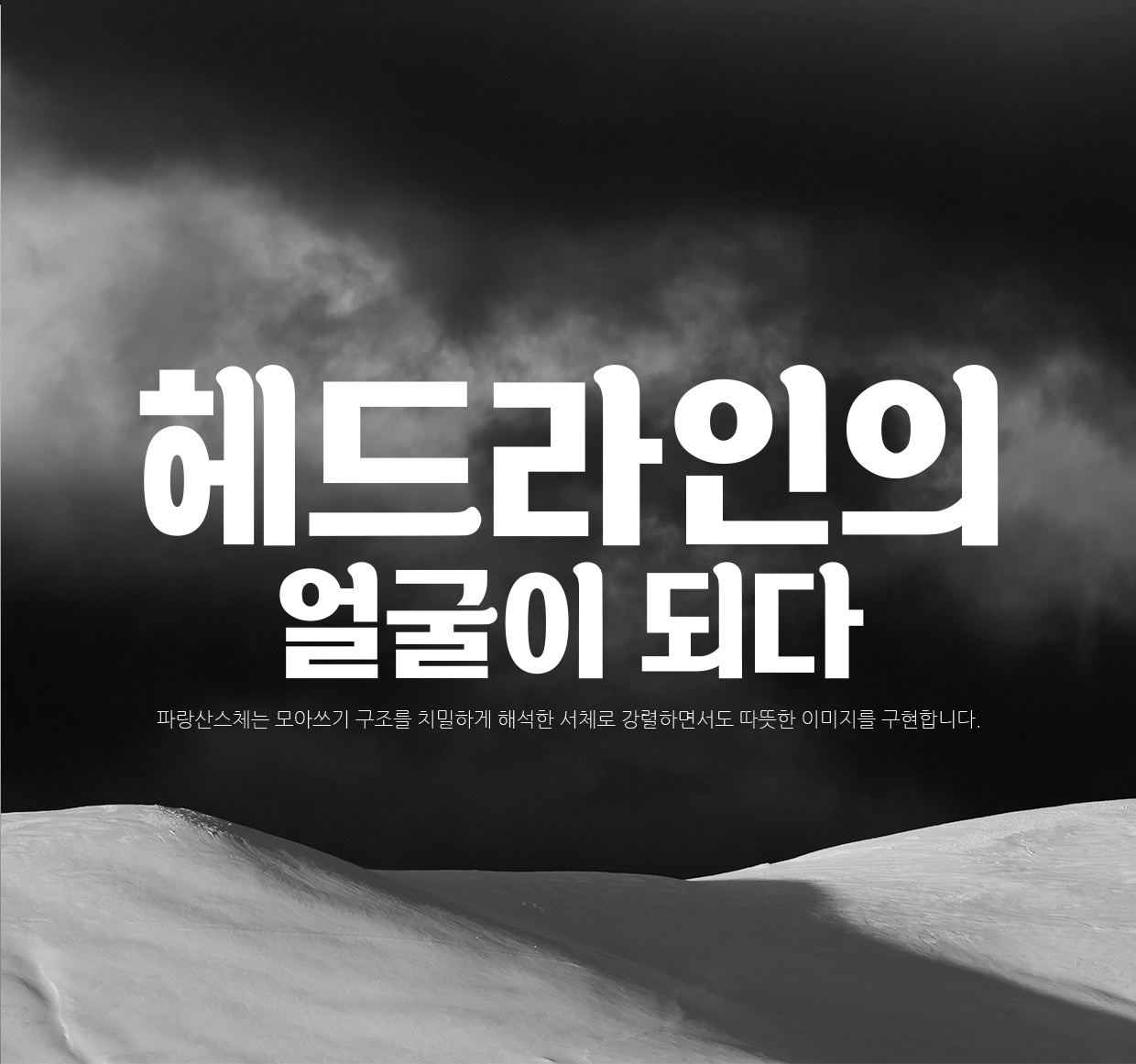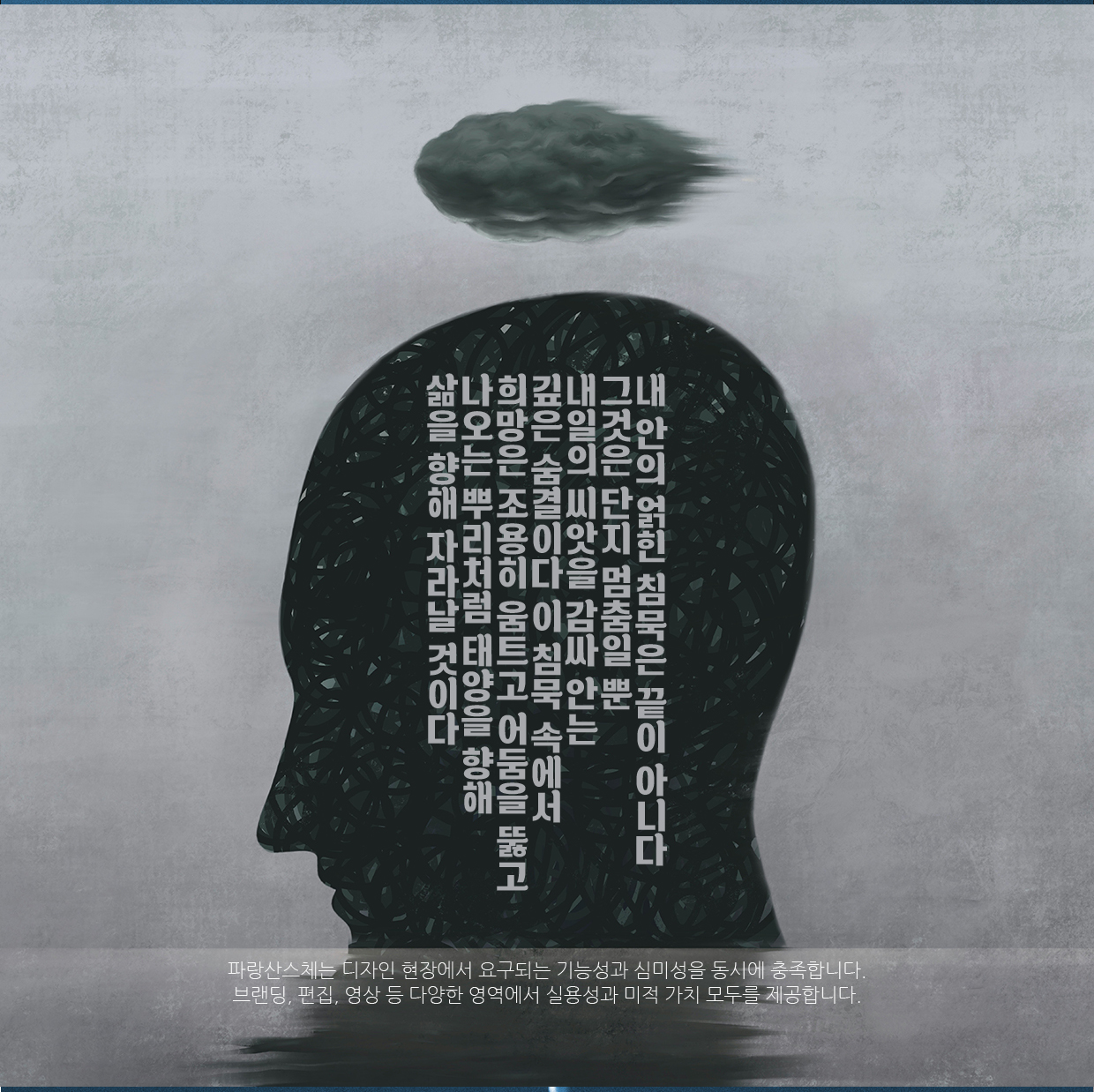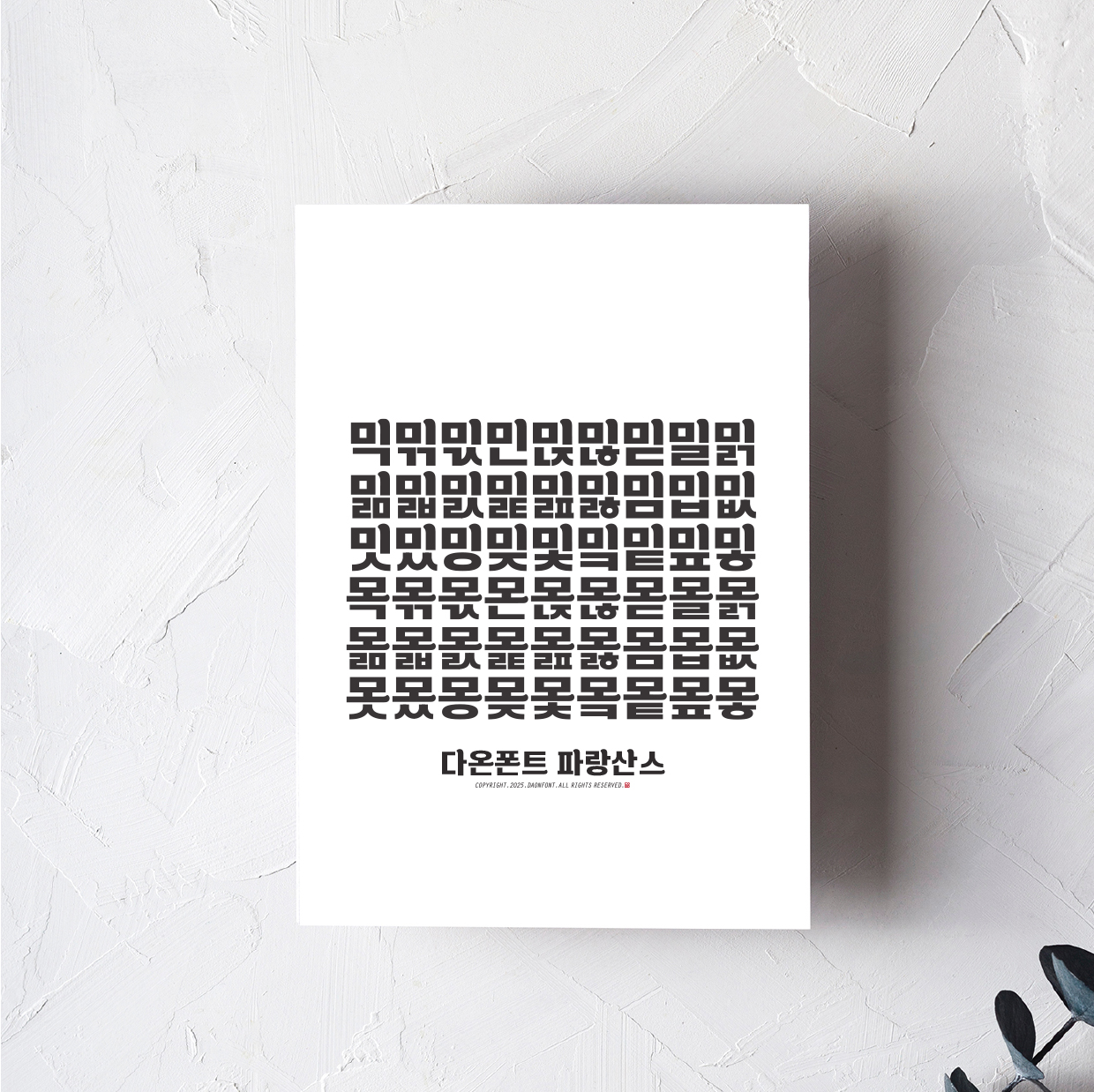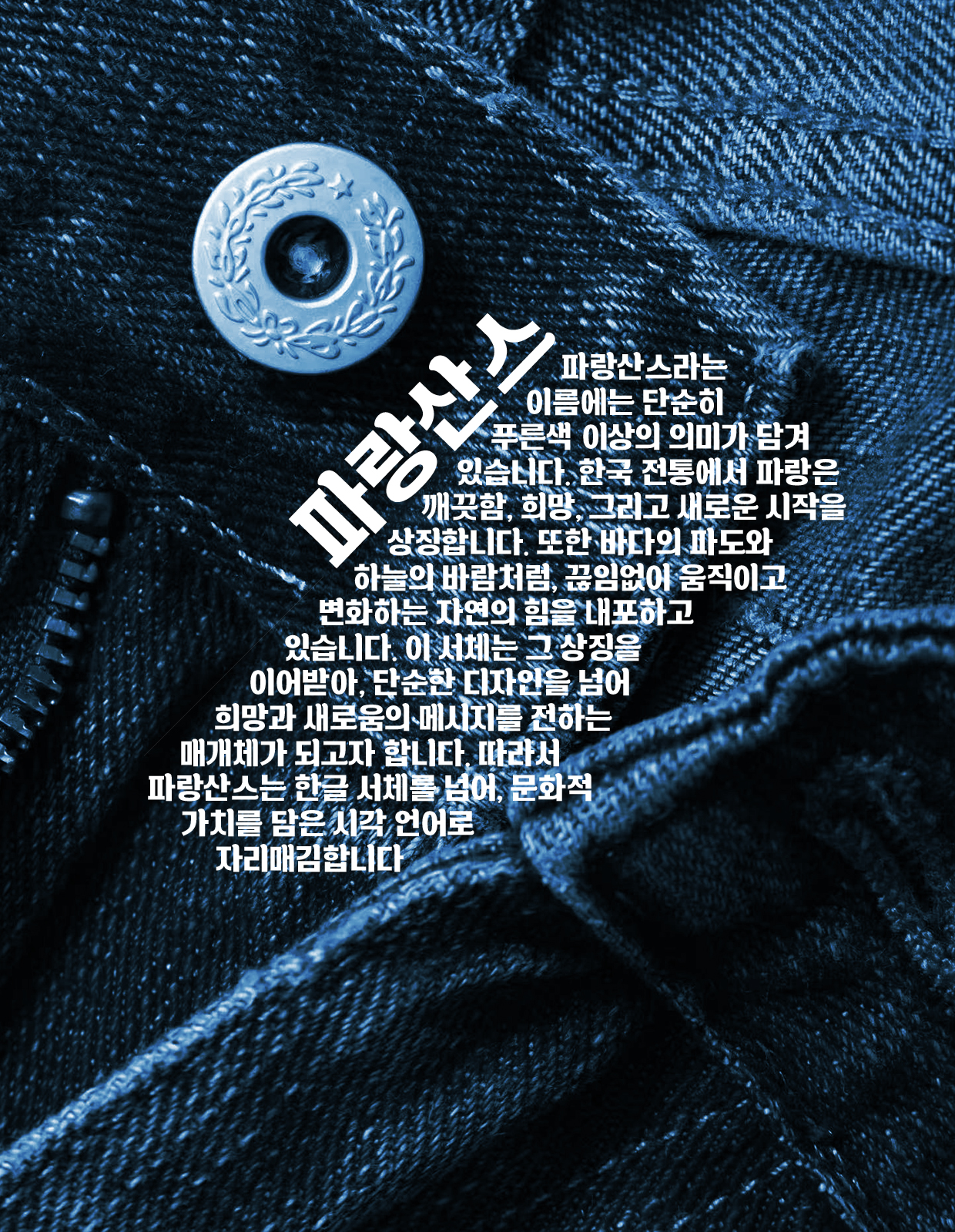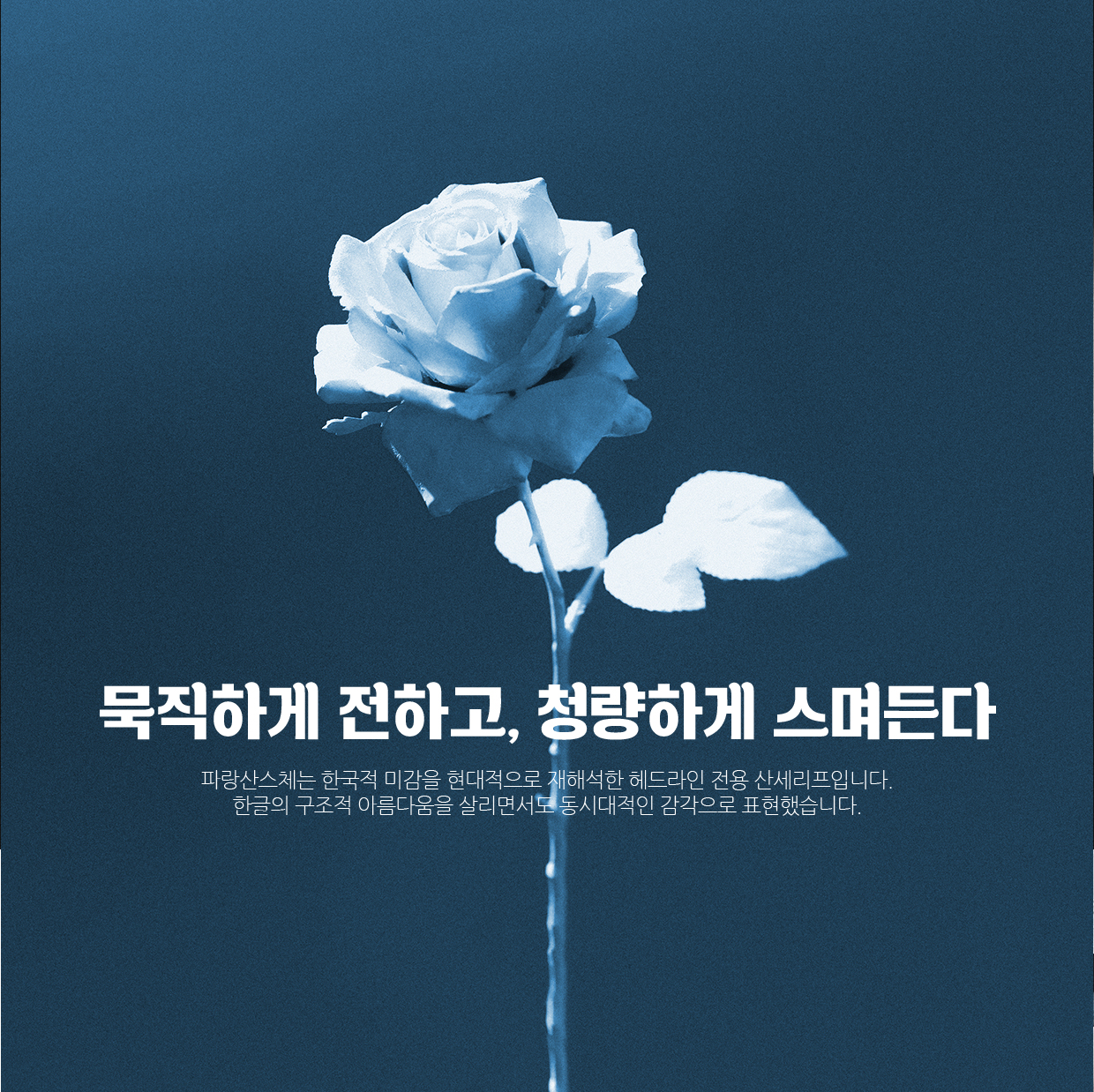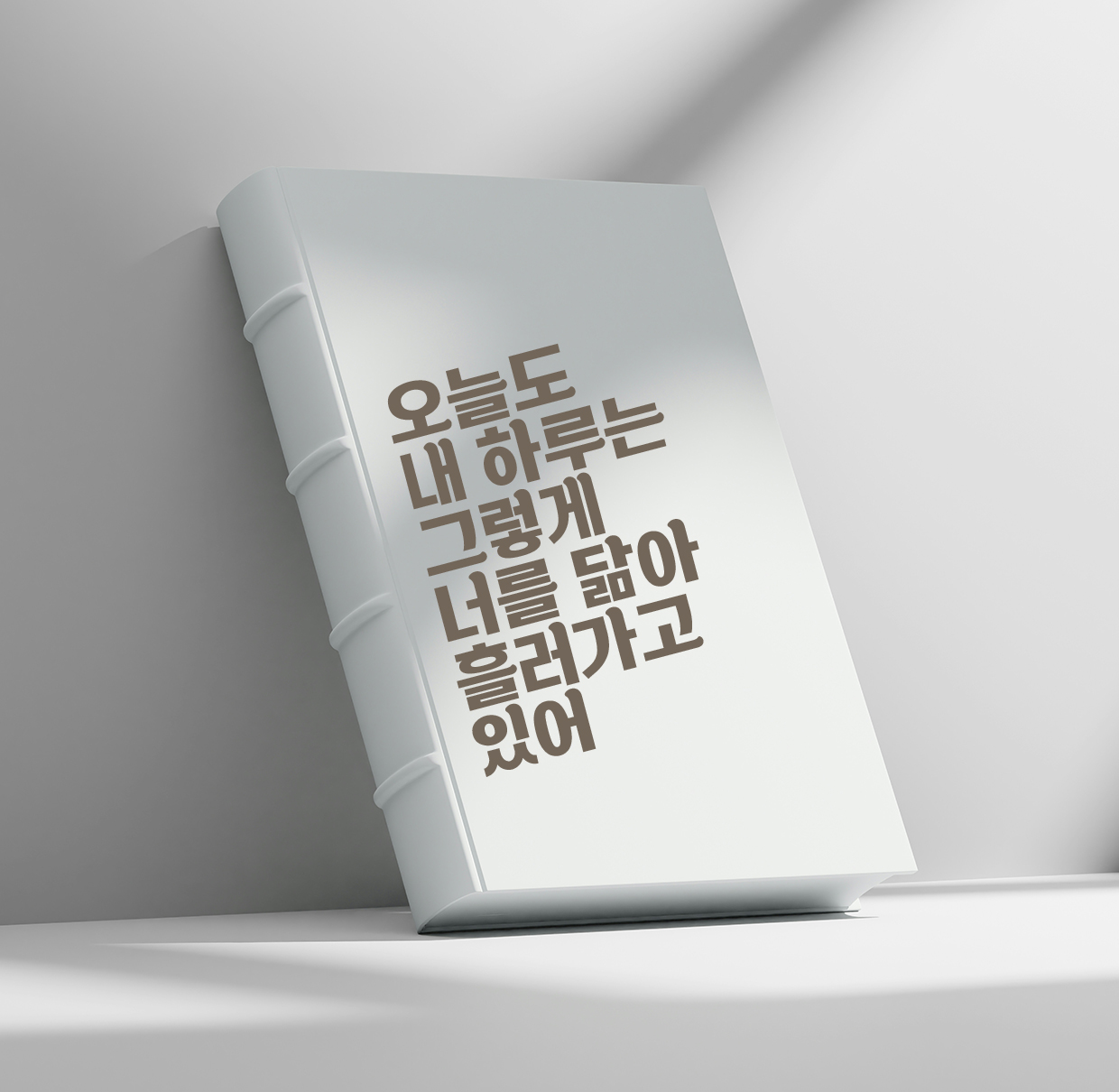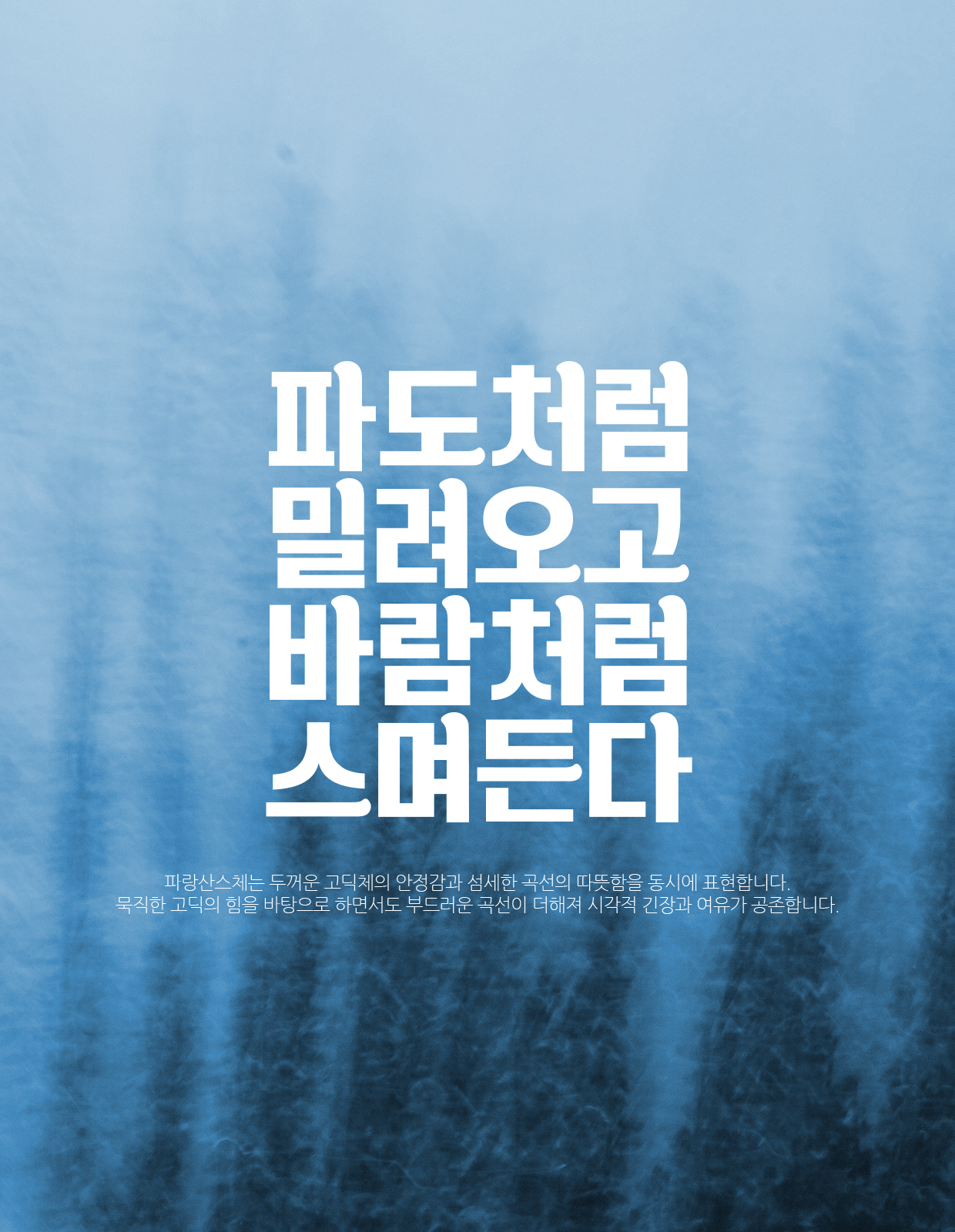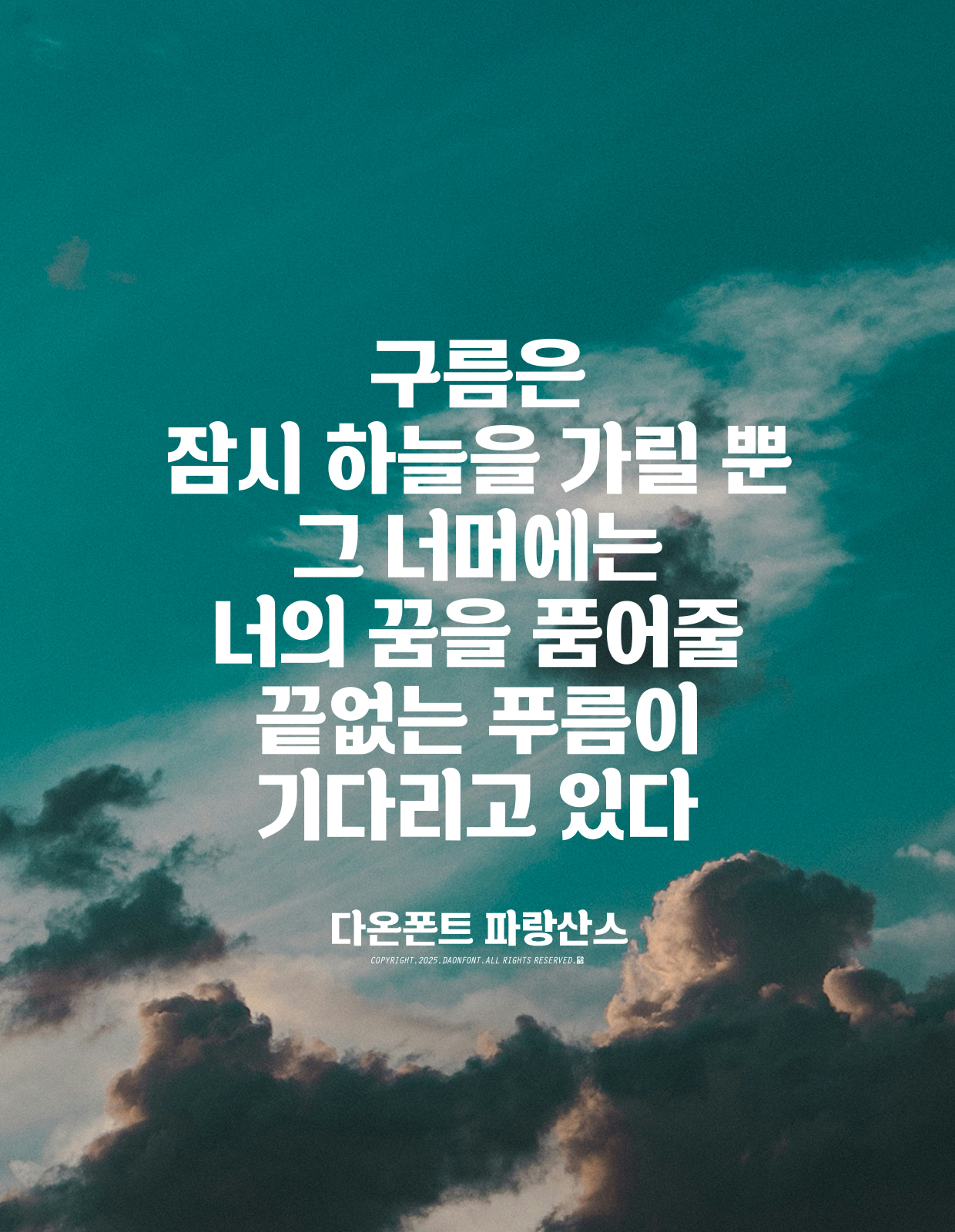
다온폰트의 신서체 파랑산스 출시안내
다온폰트의 신서체 파랑산스
이 서체의 이름은 [파랑산스]입니다.
‘파랑’은 단순히 색을 뜻하지 않습니다. 파도처럼 밀려오는 힘,
그리고 바람처럼 스며드는 자유를 함께 담은 말입니다.
여기에 산세리프(Sans Serif)의 특성을 결합하여,
단단하면서도 청량한 새로운 헤드라인 서체의 정체성을 표현했습니다.
파랑산스라는 이름에는 두 가지 의미가 동시에 담겨 있습니다.
하나는, 푸른 바다처럼 깊고 시원한 인상.
다른 하나는, 변화와 움직임을 두려워하지 않는 태도.
그래서 이 글자에는 늘 직선의 힘과 곡선의 온기가 공존합니다.
시선을 사로잡되 과하지 않고, 오래 보아도 무게감이 흐트러지지 않는.
다온폰트의 신서체 파랑산스는